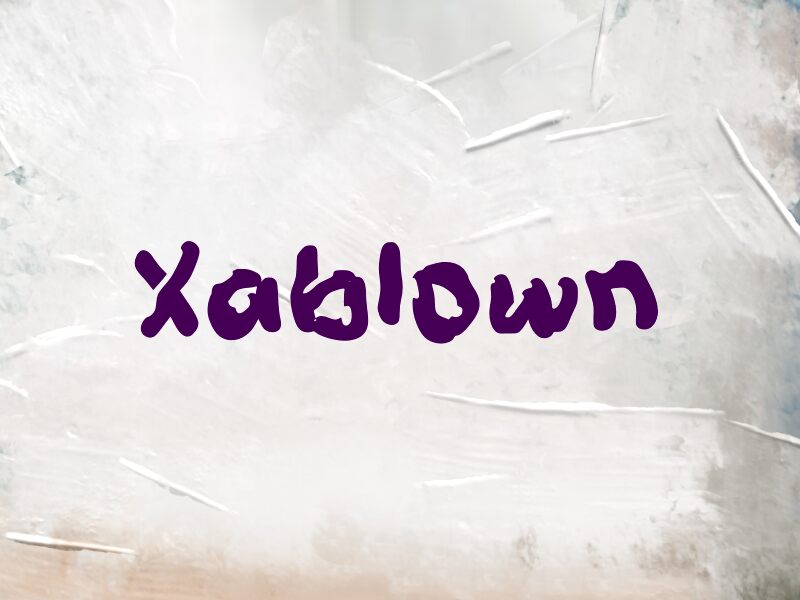
Xablown
Xablown de Wep es una tipografía display gratuita y distorsionada, definida por trazos hinchados que se expanden, se comprimen y se tambalean en cada letra. Esta silueta irregular confiere a las letras un aspecto inflado, casi excesivo, logrando que el diseño se perciba más como formas negras y orgánicas que como un corte de tipografía convencional.
Los titulares cortos, los pósteres, el arte de álbumes, los gráficos de skate y las portadas de fanzines son su hábitat natural. Su ritmo inestable y abultado también aporta carácter a diseños de pegatinas y branding de merchandising, especialmente cuando buscas letras que se sientan caóticas, infladas y un poco rebeldes en lugar de pulcras o demasiado técnicas.